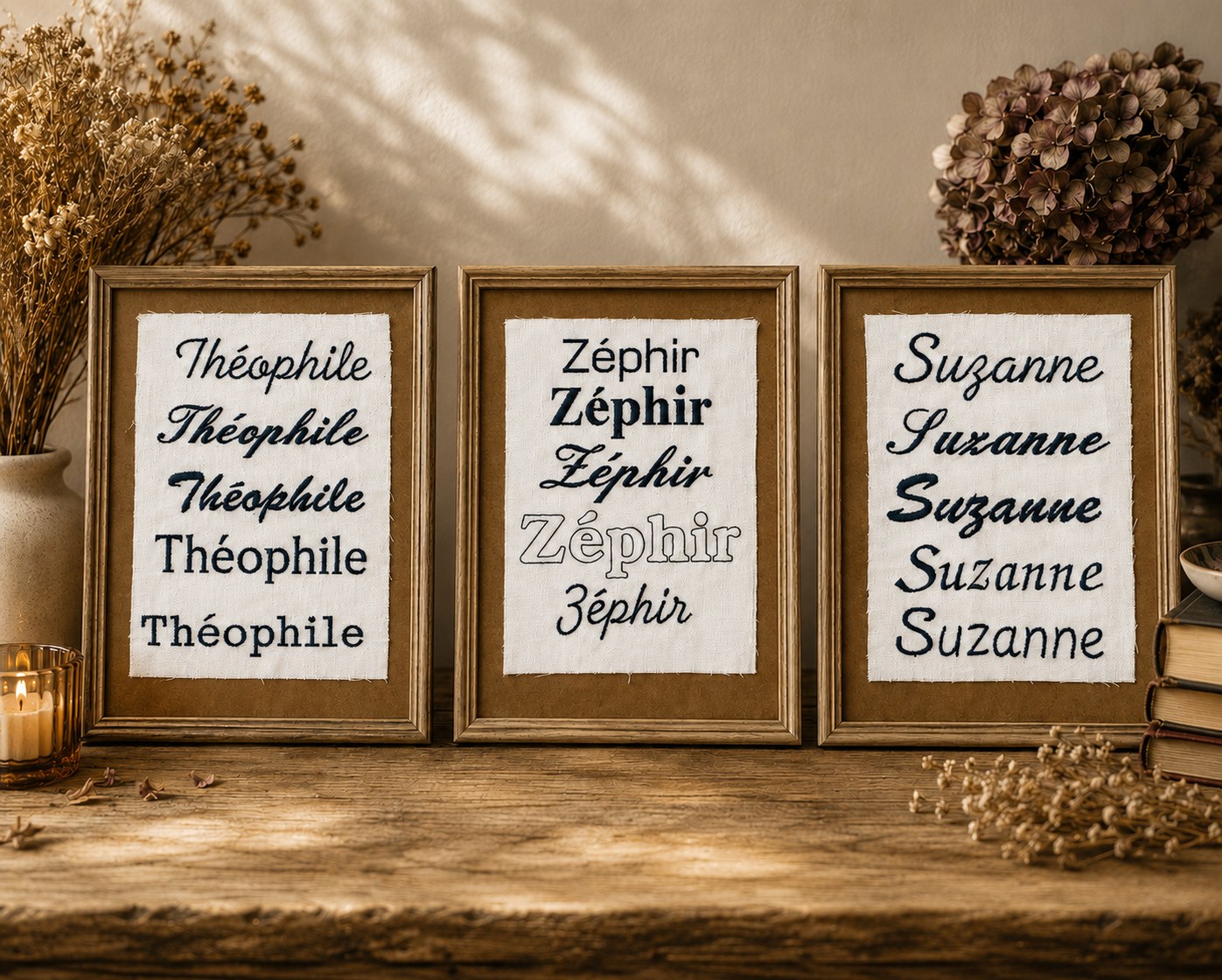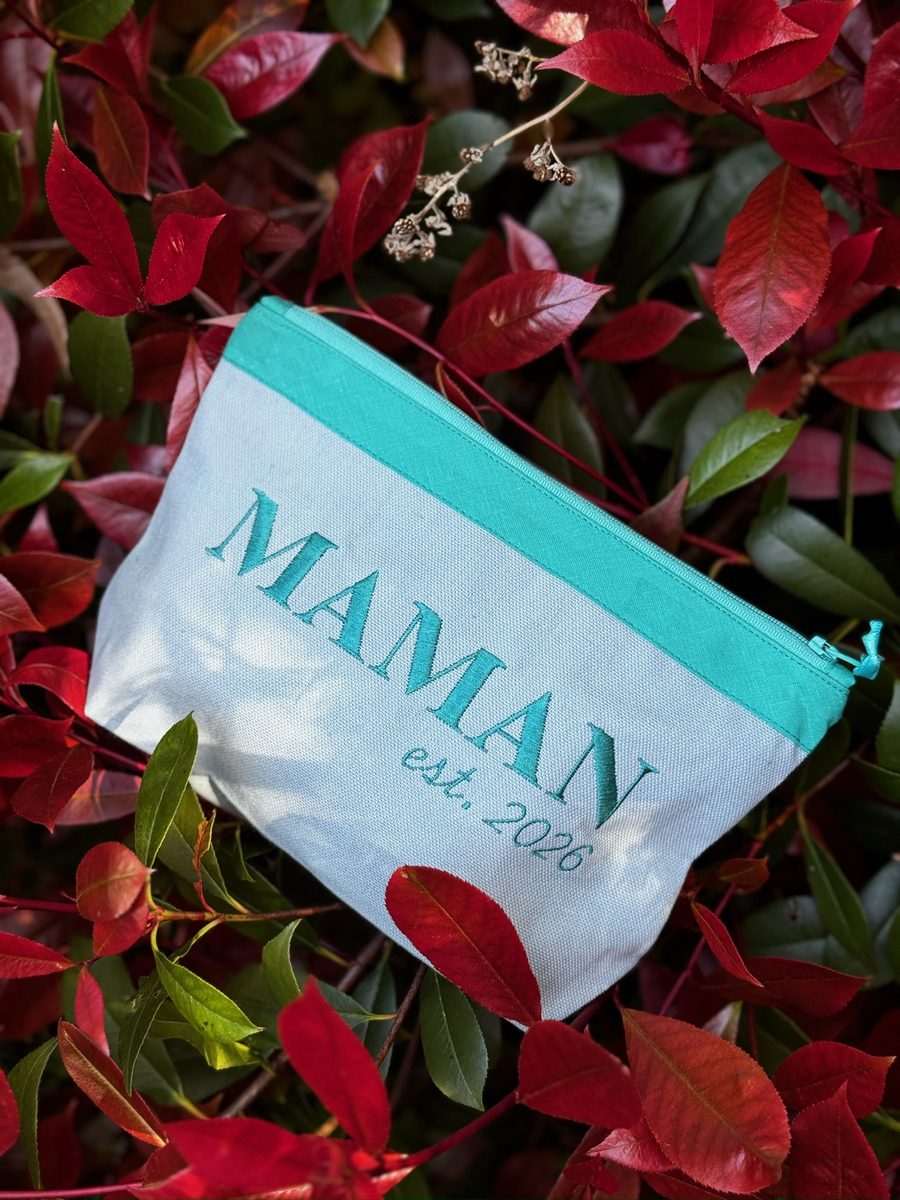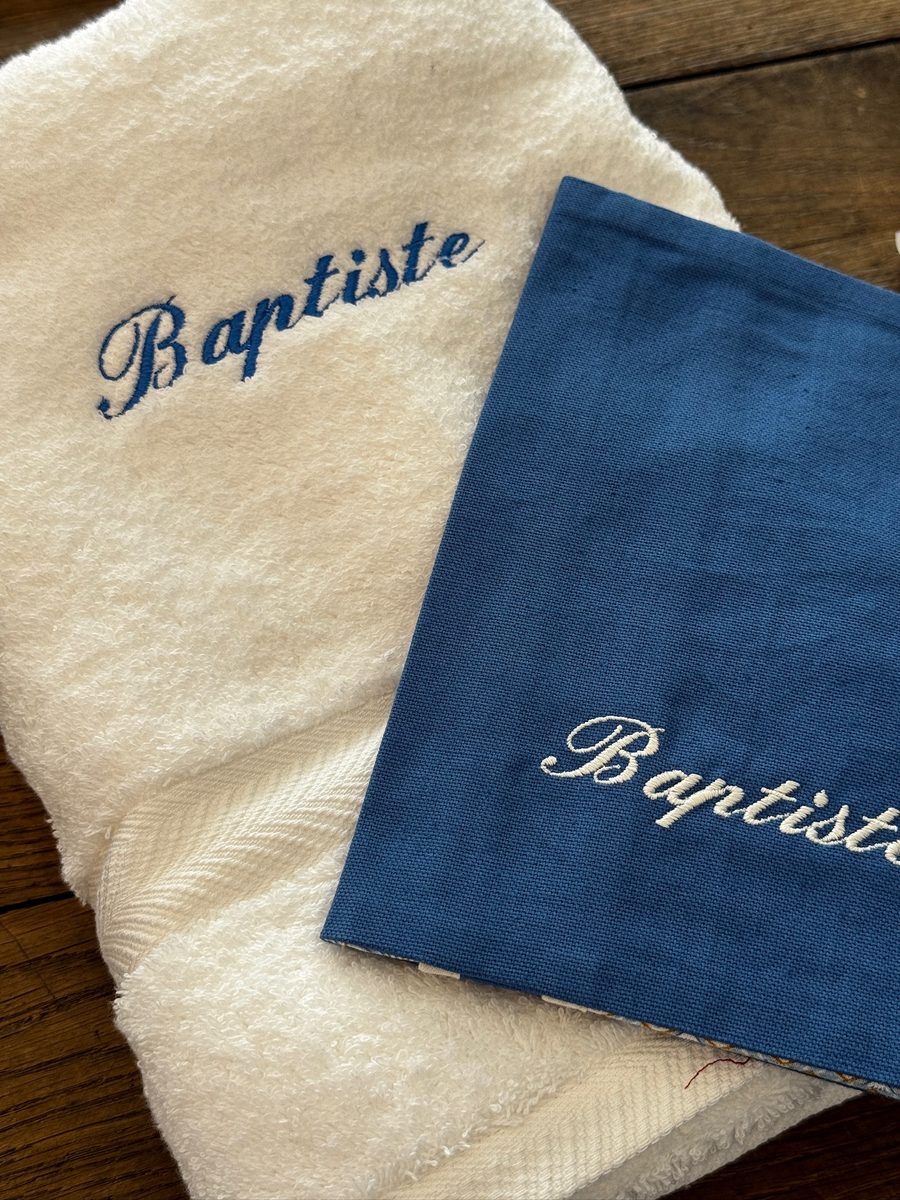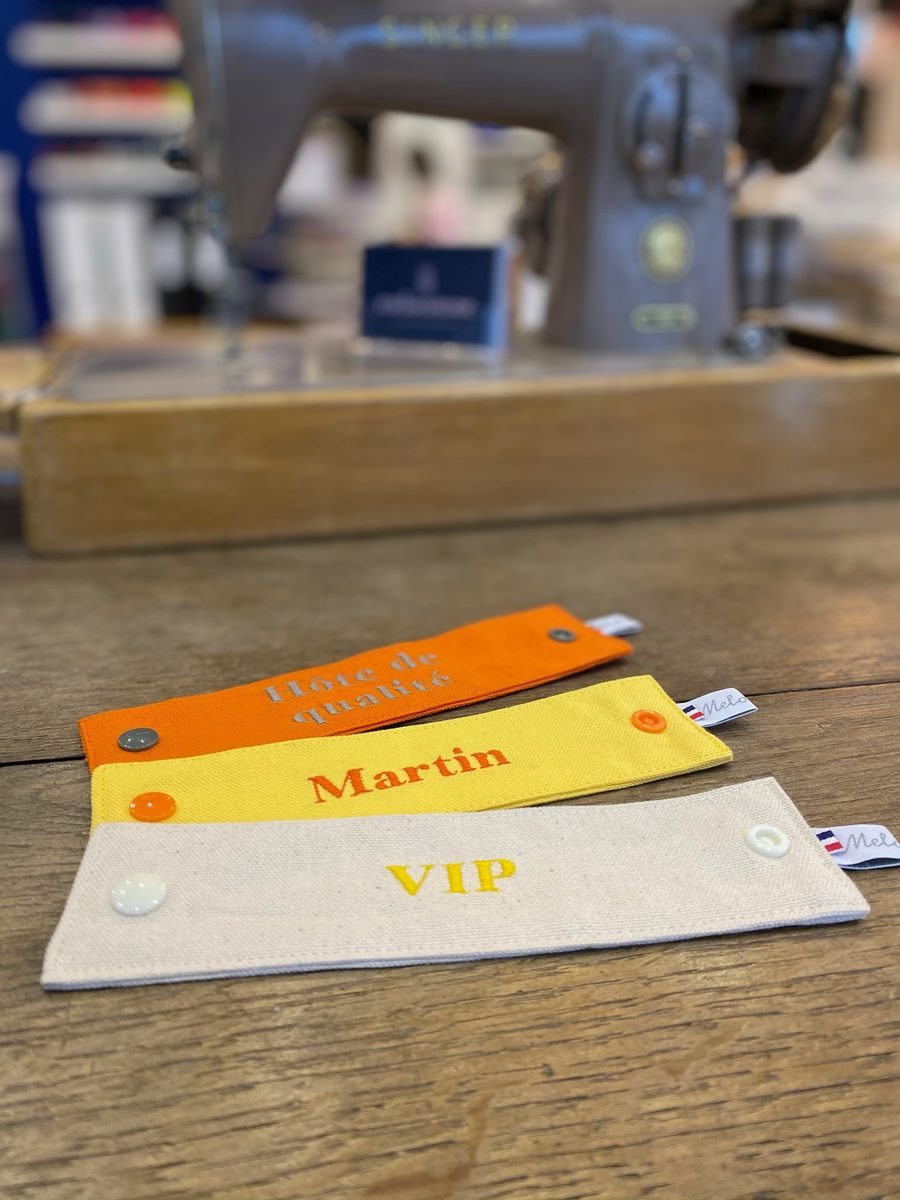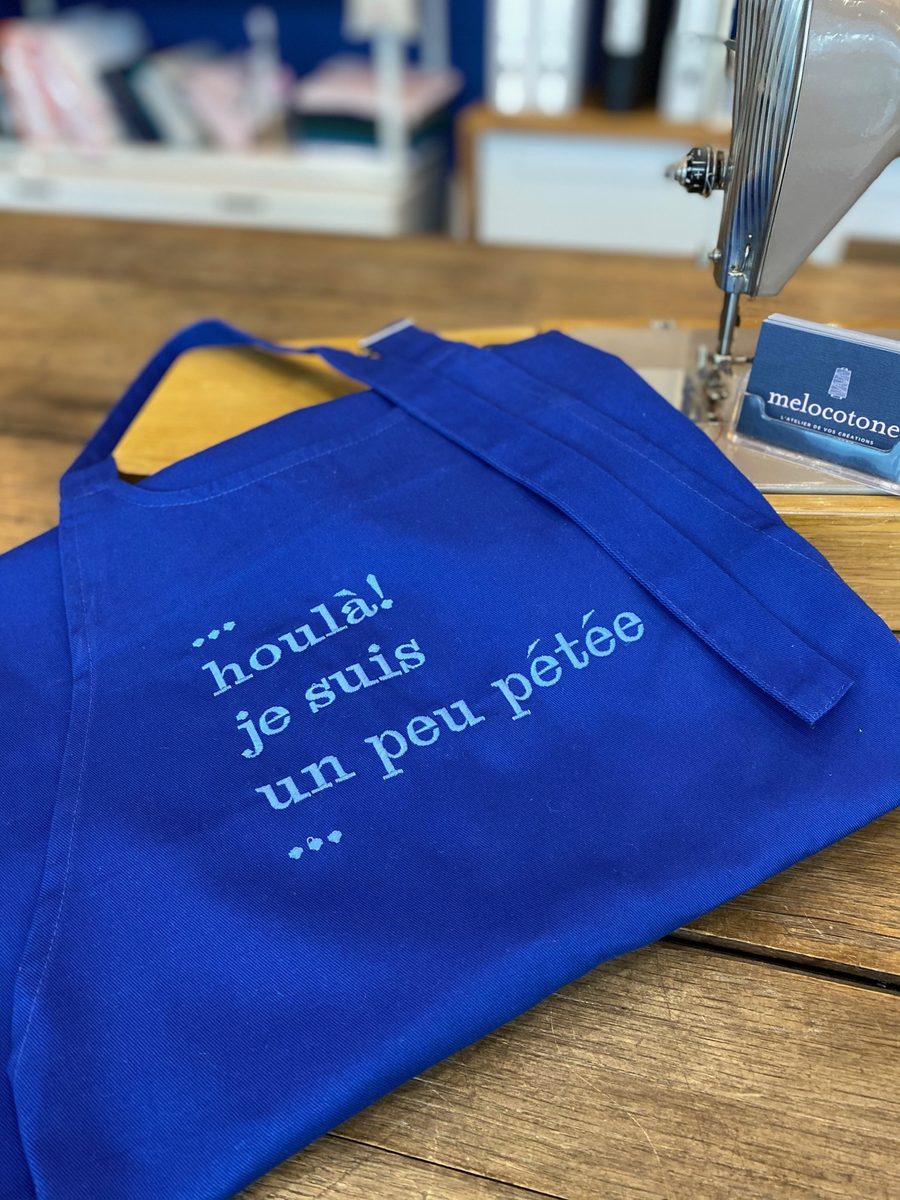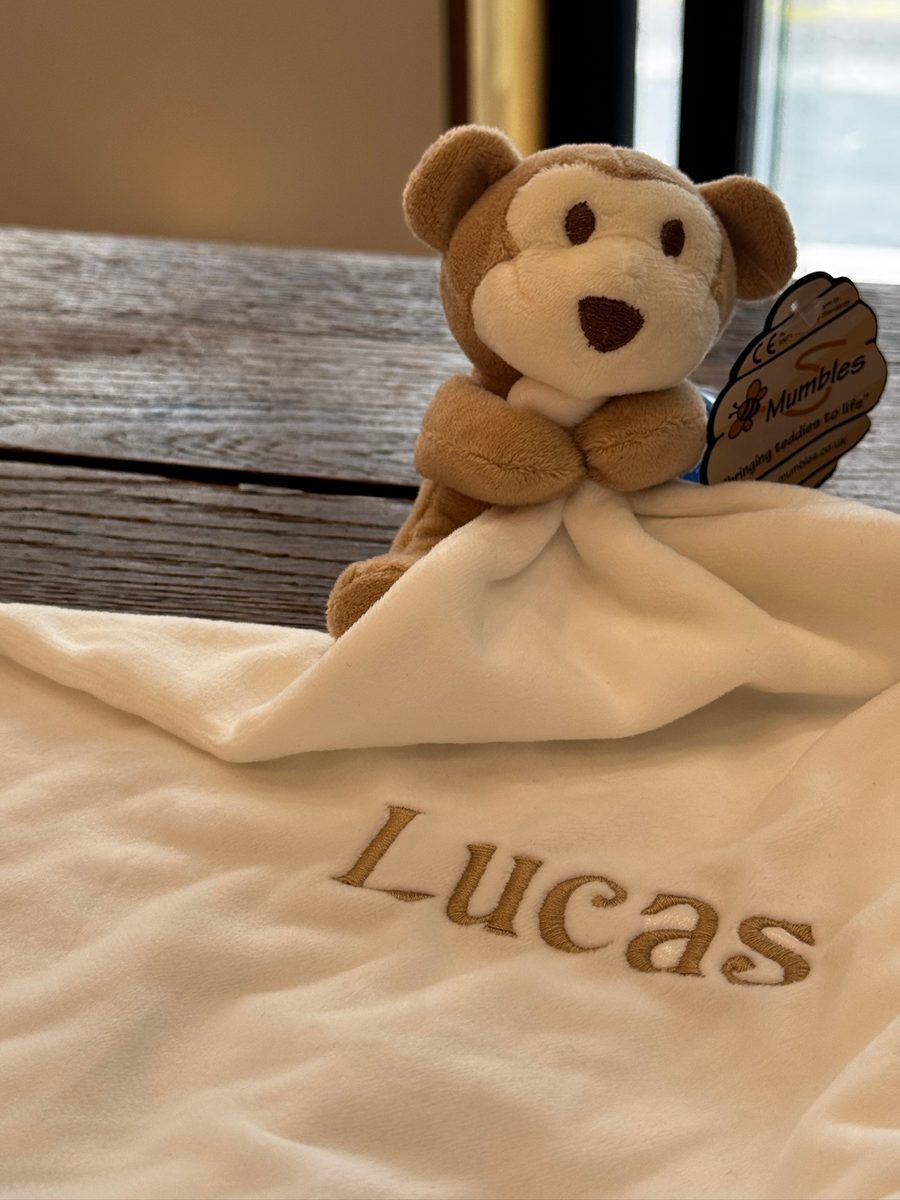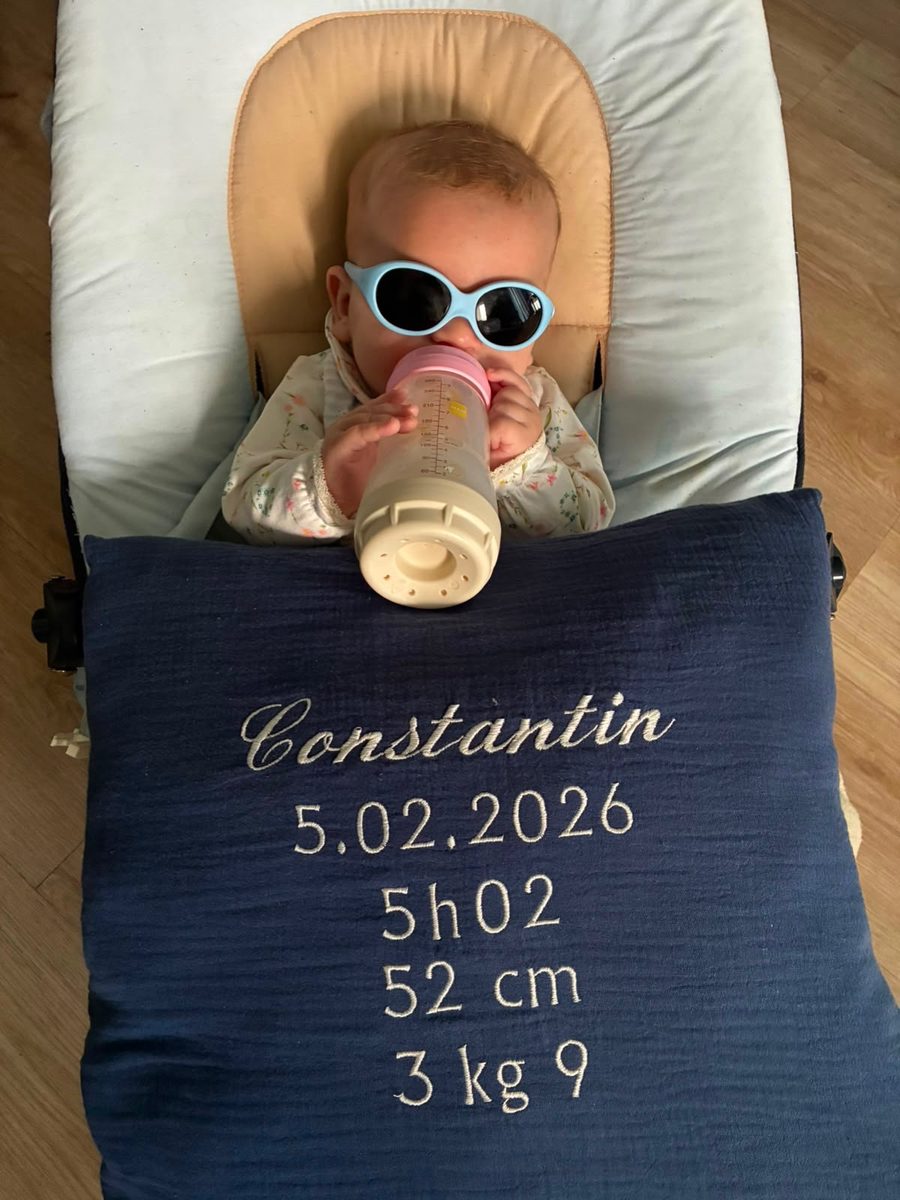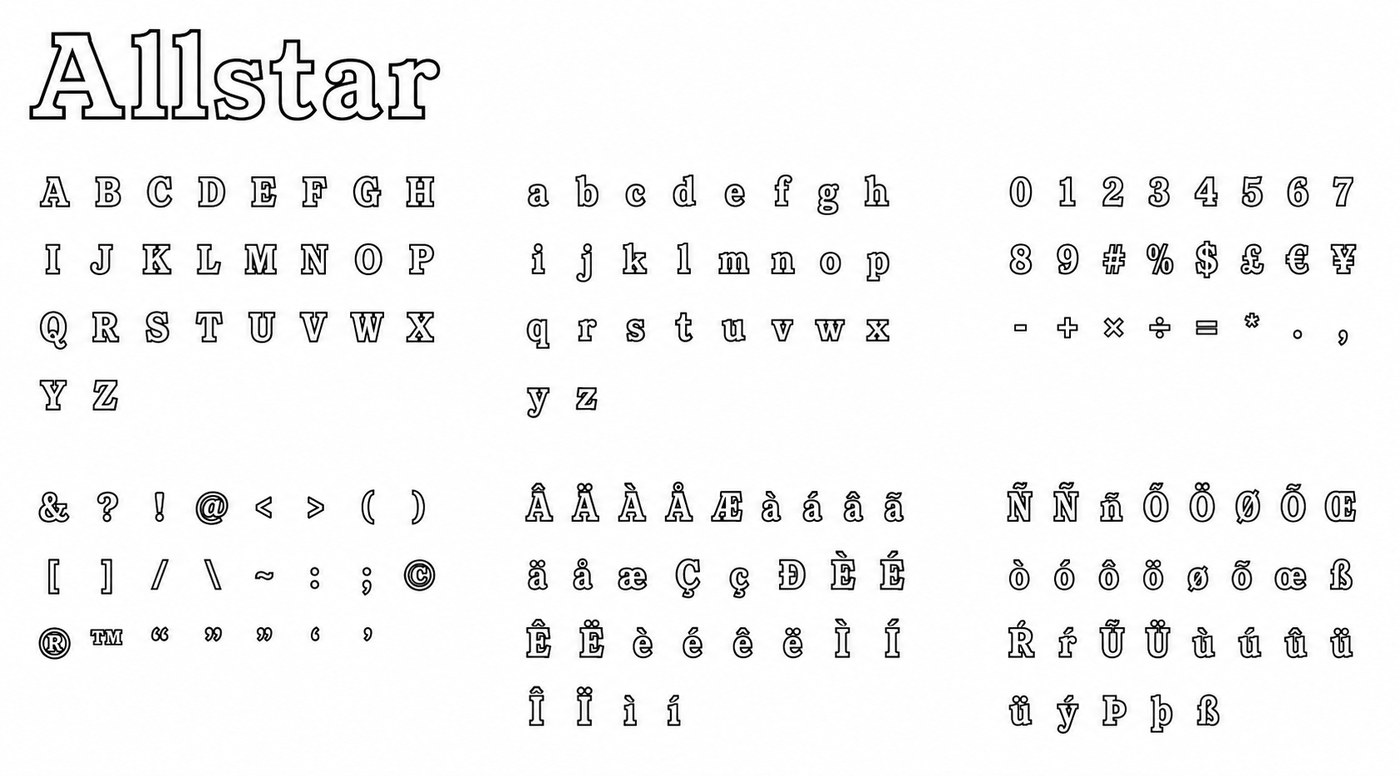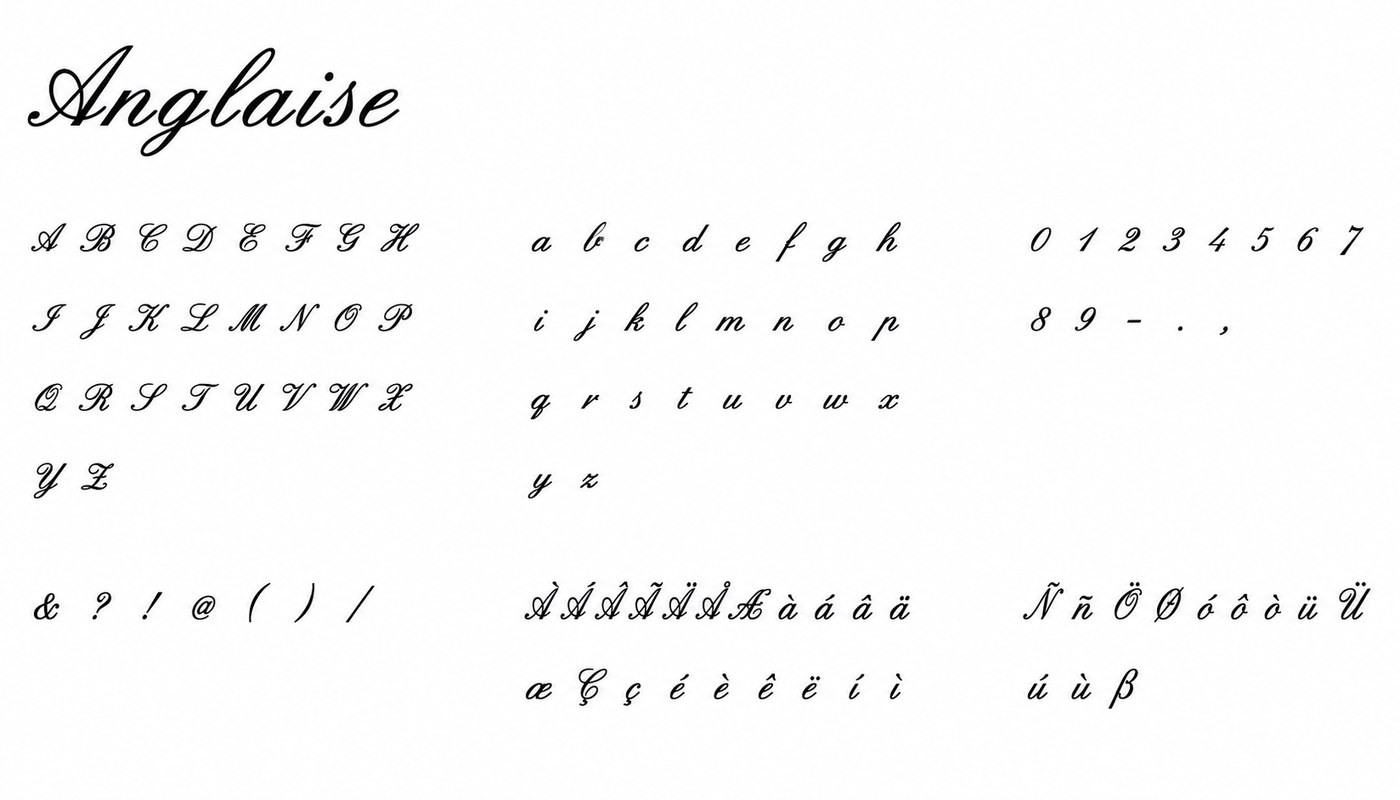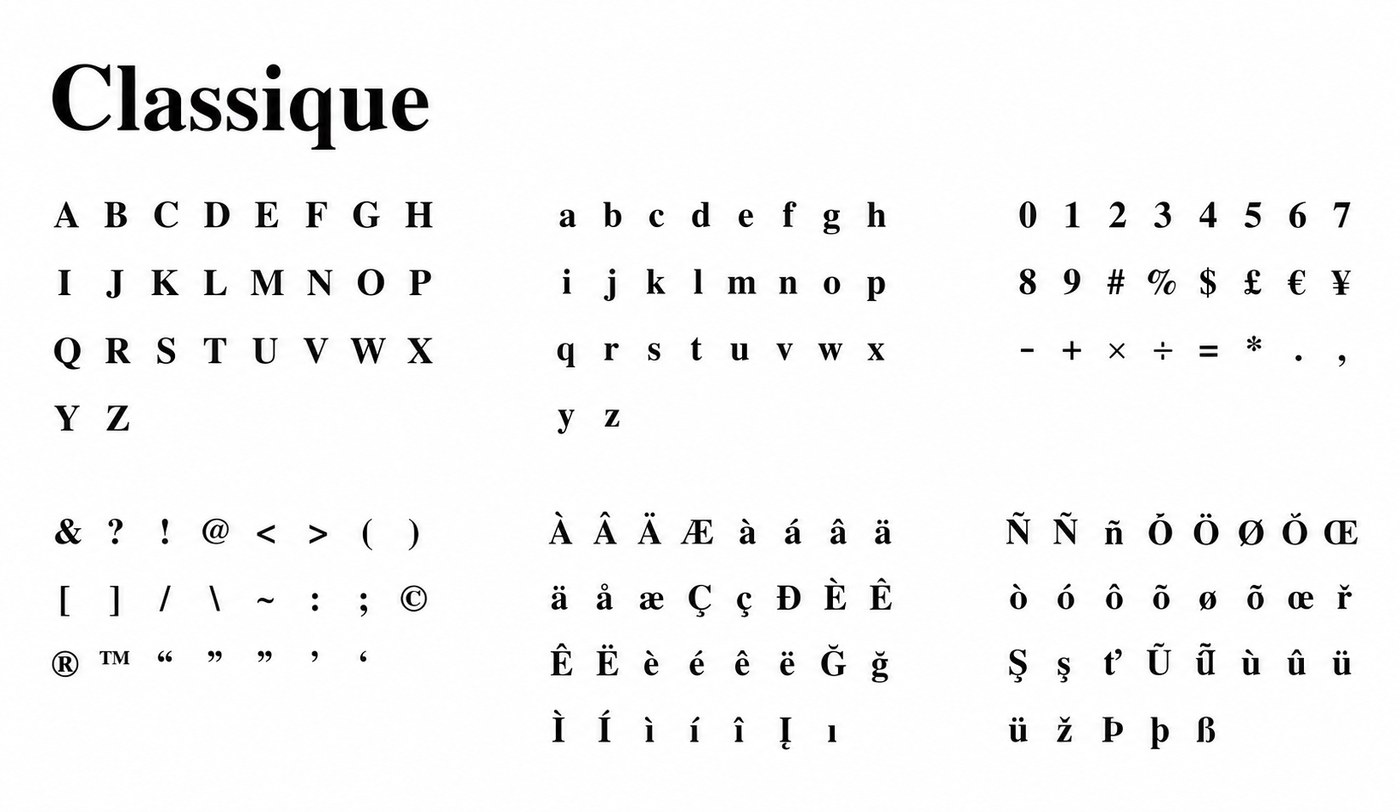
Nos typographies
Le choix de la typographie change tout : il donne le ton, l’âge, le style et parfois même l’émotion du cadeau. Voici nos inspirations, nos comparatifs et les alphabets complets pour vous aider à choisir la broderie la plus juste.
01 — Inspirations
Voir les typographies en situation
Un prénom, une initiale ou un mot ne rendent jamais pareil selon le support. Ces exemples montrent nos typographies sur des produits brodés à l’atelier.
Trousse Trio personnalisé — typographie Classique + Alamano
Classique + Alamano
Cadeau De Naissance personnalisé — typographie Anglaise
Anglaise
Cadeau De Naissance personnalisé — typographie Garden
Garden
Rond De Serviette personnalisé — typographie Classique
Classique
Tablier De Cuisine personnalisé — typographie Futura
Futura
Doudou Singe personnalisé — typographie Enfantine
Enfantine
Coussin personnalisé — typographie Anglaise + New Classique
Anglaise + New Classique
Pochette De Table personnalisé — typographie Junior
Junior
Trousse Trio personnalisé — typographie Light + Futura
Light + Futura
Trousse personnalisé — typographie Separate
Separate
Porte-Clé Cordon personnalisé — typographie Mba
Mba
Sac À Dos Kids personnalisé — typographie Classique
Classique
Cadeau De Naissance personnalisé — typographie Anglaise
Anglaise
Pochette Fourre Tout personnalisé — typographie Classique
Classique
Fouta personnalisé — typographie Classique
Classique
Trousse personnalisé — typographie Classique
Classique
Pochette Serviette De Table personnalisé — typographie Alamano
Alamano
Maxi Trousse personnalisé — typographie Garden
Garden
Body personnalisé — typographie Alamano
Alamano
Pochette Brosse À Dents personnalisé — typographie Classique
Classique